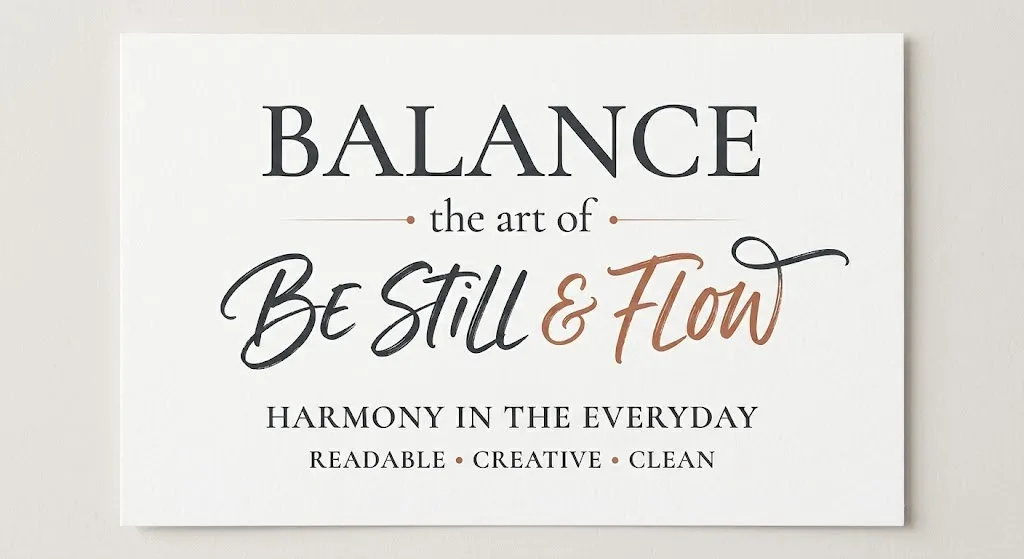
Stylische Schriftarten für TikTok-Beschriftungen helfen dabei, mehr Aufmerksamkeit, Klicks und Engagement zu erzielen. Du kannst fancy Fonts mit Unicode-Generatoren erstellen und direkt in TikTok einfügen. Besonders gut funktionieren auffällige, kreative und leicht lesbare Schriftarten, die deine Inhalte visuell hervorheben.
Auf TikTok entscheiden oft nur wenige Sekunden darüber, ob jemand dein Video anschaut oder direkt weiterscrollt. Nutzer bewegen sich extrem schnell durch den Feed – Inhalte müssen sofort ins Auge fallen, sonst gehen sie im Strom neuer Videos unter.
Genau hier spielen Beschriftungen (Captions) eine entscheidende Rolle. Eine auffällige, stylische Schrift kann den Unterschied machen: Sie zieht Aufmerksamkeit an, vermittelt Emotionen und motiviert Nutzer, länger zu bleiben oder zu interagieren. Gute TikTok-Captions sind nicht nur Text – sie sind ein wichtiger Teil deiner Content-Strategie.
Außerdem werden TikTok-Inhalte nicht nur innerhalb der App entdeckt. Viele Nutzer suchen gezielt nach Trends und Ideen über Google Search oder die integrierte TikTok-Suche. Mit den richtigen Keywords und kreativen Schriftarten kannst du deine Sichtbarkeit deutlich steigern und mehr Reichweite erzielen.
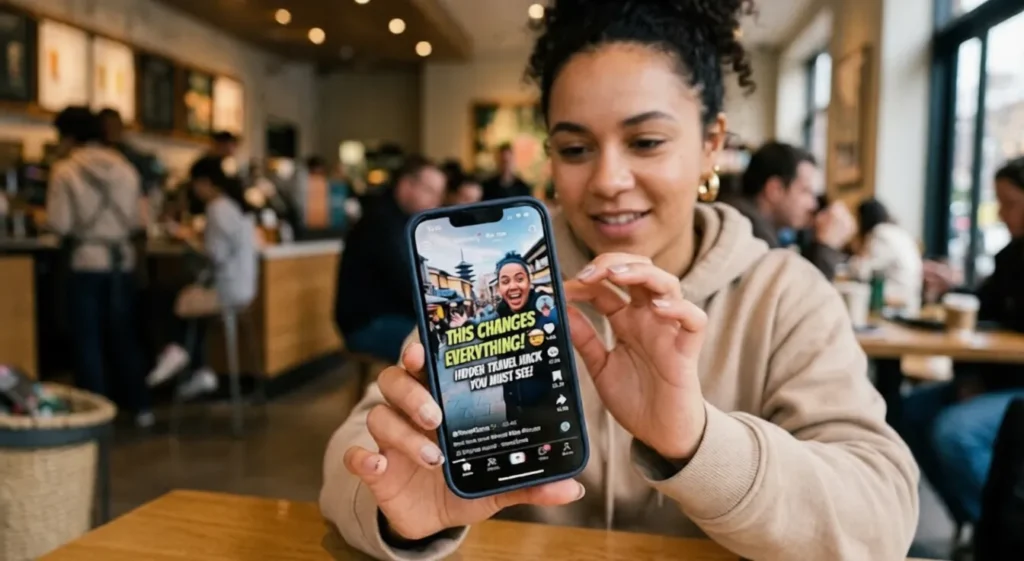
Warum stylische Schriftarten auf TikTok wichtig sind
Stylische Schriftarten sind auf TikTok sehr wichtig, weil sie deine Videos sofort auffälliger machen und mehr Engagement bringen.
Aufmerksamkeit in den ersten Sekunden
Nutzer scrollen schnell durch TikTok. Auffällige Schriftarten stoppen den Scroll und ziehen sofort Aufmerksamkeit auf dein Video.
Einfluss auf Engagement & Watch Time
Gut lesbare und kreative Texte sorgen dafür, dass Nutzer länger schauen und mehr interagieren (Likes, Kommentare). Besonders wichtig, da viele Videos ohne Ton geschaut werden.
Branding und Wiedererkennung
Wenn du immer ähnliche Schriftarten nutzt, erkennen Nutzer deine Inhalte schneller wieder. Das stärkt deine Marke. Tools wie CapCut helfen dir dabei.
SEO & Sichtbarkeit
Mit Texten und Keywords in deinen Videos kannst du besser in der TikTok-Suche und bei Google Search gefunden werden.
Die besten Schriftarten für TikTok-Beschriftungen
Die richtige Schriftart kann dein Video auf TikTok deutlich hervorheben. Hier sind die besten Arten von Schriftarten, die gut funktionieren:
Auffällige & fette Schriftarten
Diese Fonts sind perfekt, um sofort Aufmerksamkeit zu bekommen. Sie sind groß, klar und wirken stark – ideal für wichtige Botschaften oder Hooks am Anfang des Videos.
Minimalistische & cleane Fonts
Einfache Schriftarten sind leicht zu lesen und wirken professionell. Sie eignen sich besonders gut für informative Inhalte oder wenn du deine Botschaft klar vermitteln willst.
Kreative & dekorative Schriftarten
Diese Schriftarten geben deinem Content Persönlichkeit. Sie sind verspielt, einzigartig und helfen dabei, Emotionen zu zeigen und sich von anderen Videos abzuheben.
Kombination aus Emojis & Text
Die Mischung aus Text und Emojis macht deine Beschriftungen lebendiger und ansprechender. Emojis helfen, Gefühle zu zeigen und wichtige Punkte hervorzuheben.
Wie man stylische Schriftarten für TikTok erstellt
Stylische Schriftarten für TikTok zu erstellen ist einfacher, als viele denken. Du kannst dafür Online-Tools, Apps oder die integrierten Funktionen von TikTok nutzen.
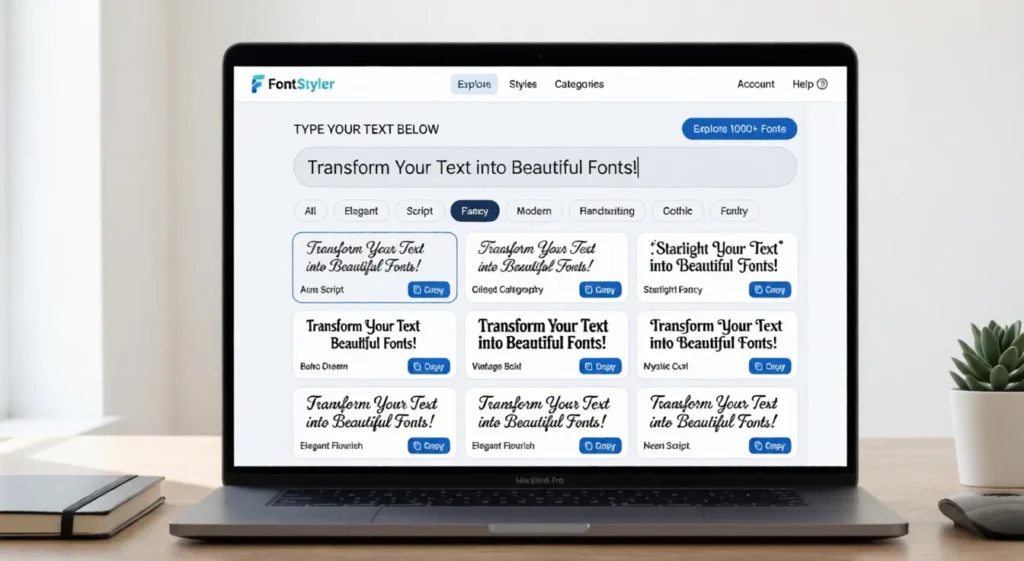
Font Generator Tools (Unicode-based)
Mit Online-Generatoren kannst du schnell fancy Schriftarten erstellen. Tools wie Creative Fabrica oder Fotor funktionieren so:
- Text eingeben
- Stil auswählen
- Kopieren & in TikTok einfügen
Das ist die schnellste Methode für stylische Texte.
Copy & Paste Methode
Viele dieser Schriftarten basieren auf Unicode. Das bedeutet, du kannst sie einfach kopieren und direkt in deine TikTok-Captions oder Videos einfügen – ohne extra Designkenntnisse.
Mobile Apps für Text-Styling
Apps wie CapCut bieten noch mehr Möglichkeiten:
- Eigene Schriftarten (TTF/OTF) importieren
- Text-Animationen hinzufügen
- Kreative Effekte (z. B. Text hinter Personen) erstellen
Integrierte TikTok-Funktionen
TikTok selbst bietet bereits viele Optionen:
- Verschiedene Schriftarten, Farben und Hintergründe
- Automatische Untertitel mit anpassbaren Styles
- Beliebte Schrift wie „TikTok Sans“ für klare Lesbarkeit
Beispiele für virale TikTok-Beschriftungen
Virale Captions auf TikTok sind kurz, emotional und machen neugierig. Sie bringen Nutzer dazu, länger zu schauen und zu interagieren. Tools wie CapCut helfen dabei, solche Texte kreativ umzusetzen.
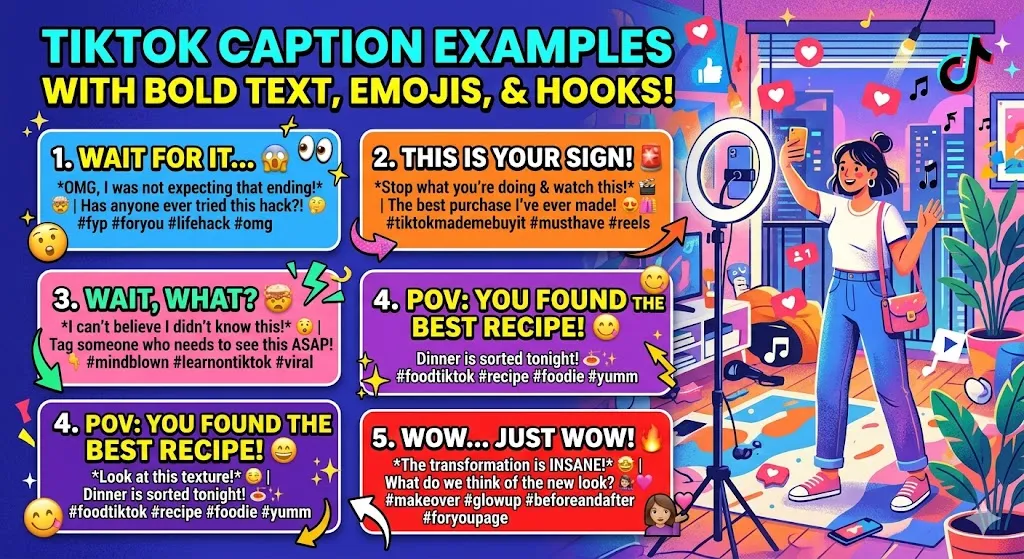
Kurze, emotionale Hooks
Diese Texte sind schnell verständlich und ziehen sofort Aufmerksamkeit:
- „Einfach wow.“
- „Ich bin sprachlos.“
- „Zu gut…“
- „Wartet darauf…“
👉 Kurz & klar = mehr Views
Trendbasierte Texte
Diese nutzen aktuelle Trends und steigern die Viralität:
Es ist wichtig, verschiedene Schriftarten und Stile zu testen, um herauszufinden, was bei deiner Zielgruppe am besten funktioniert. Trends ändern sich schnell – daher lohnt es sich, regelmäßig neue Designs auszuprobieren.
Achte dabei immer auf die richtige Balance zwischen Kreativität und Lesbarkeit. Zu viel Design kann verwirren, während klare und gut lesbare Texte deine Inhalte erfolgreicher machen.